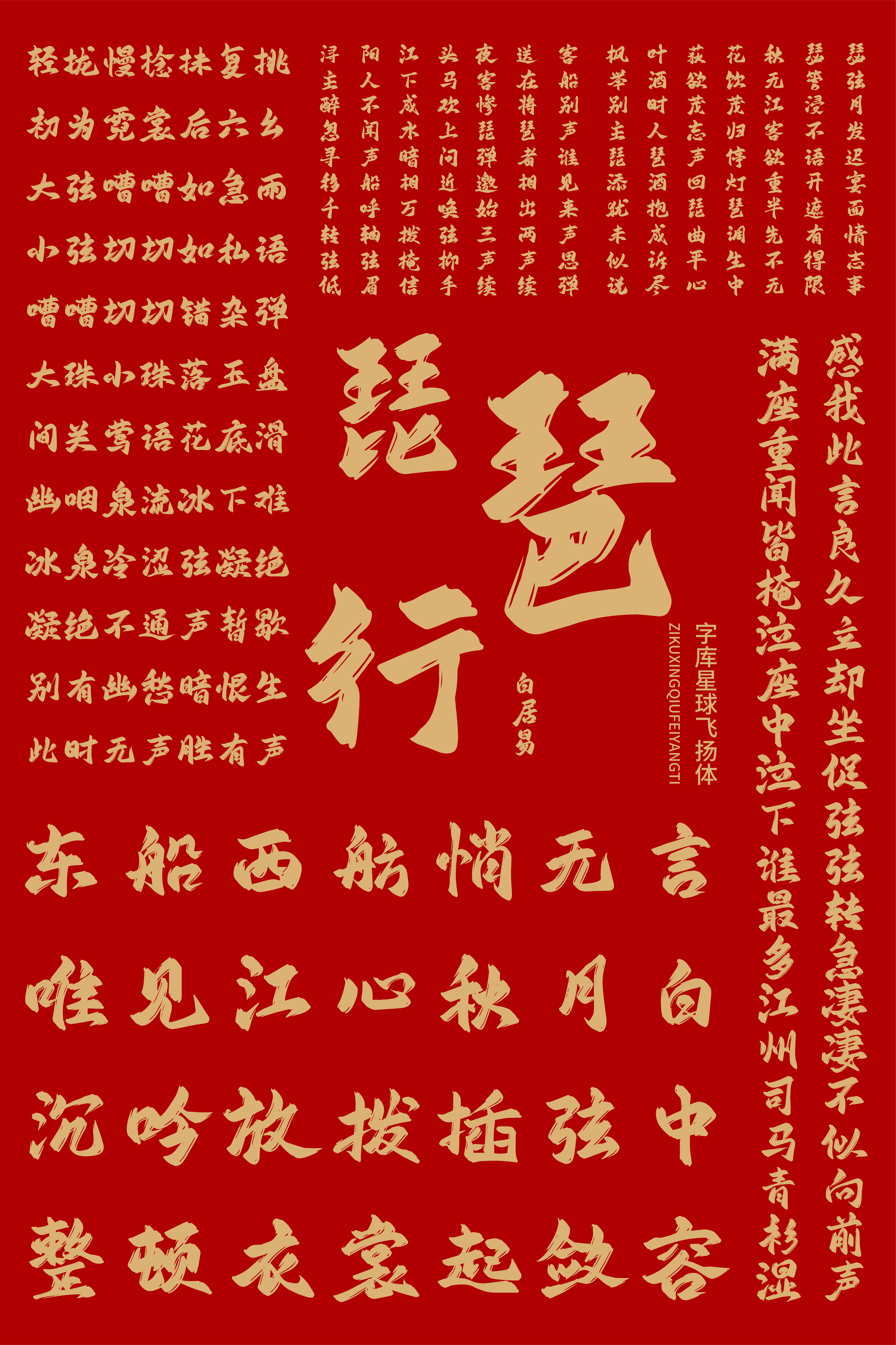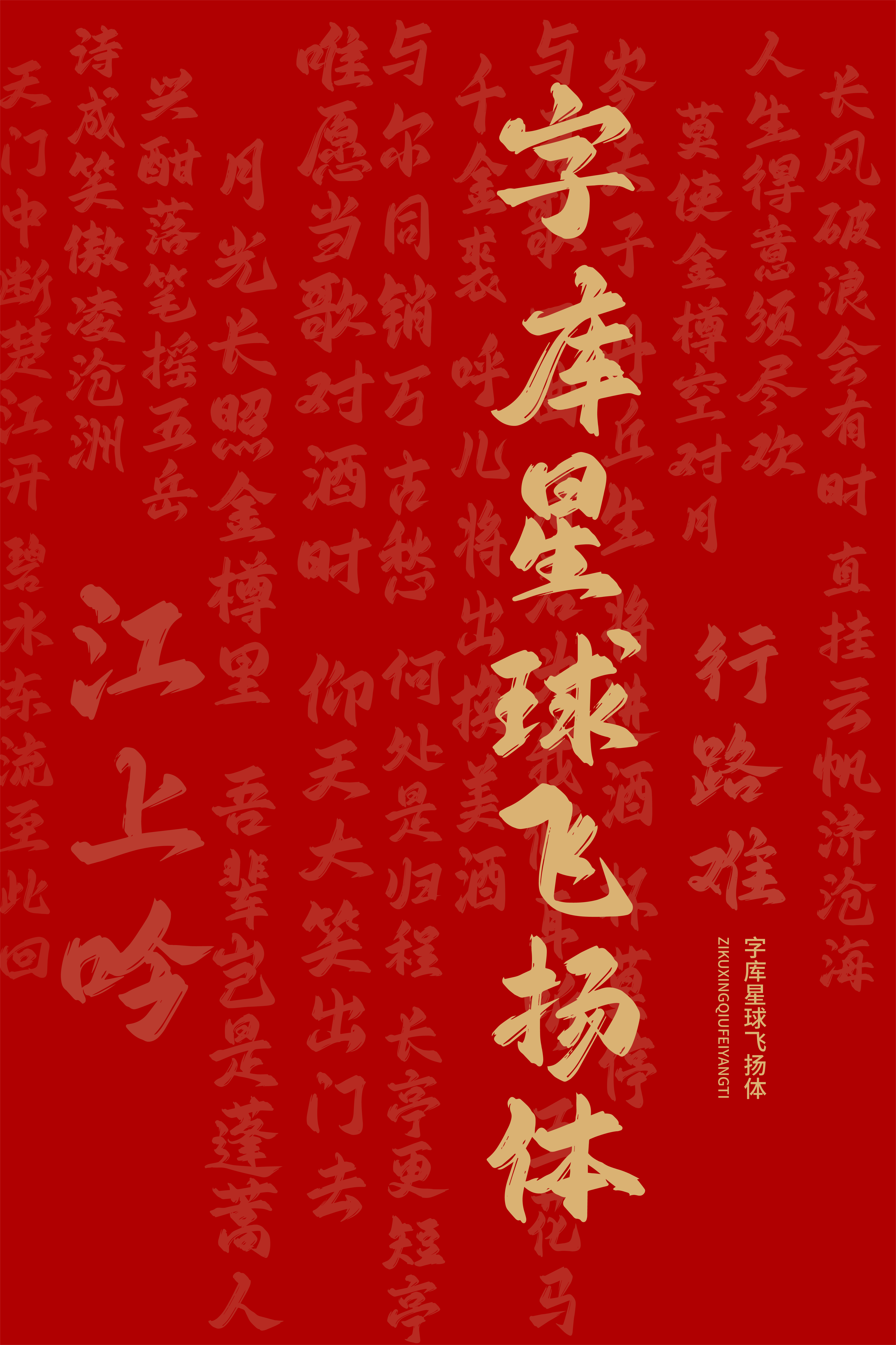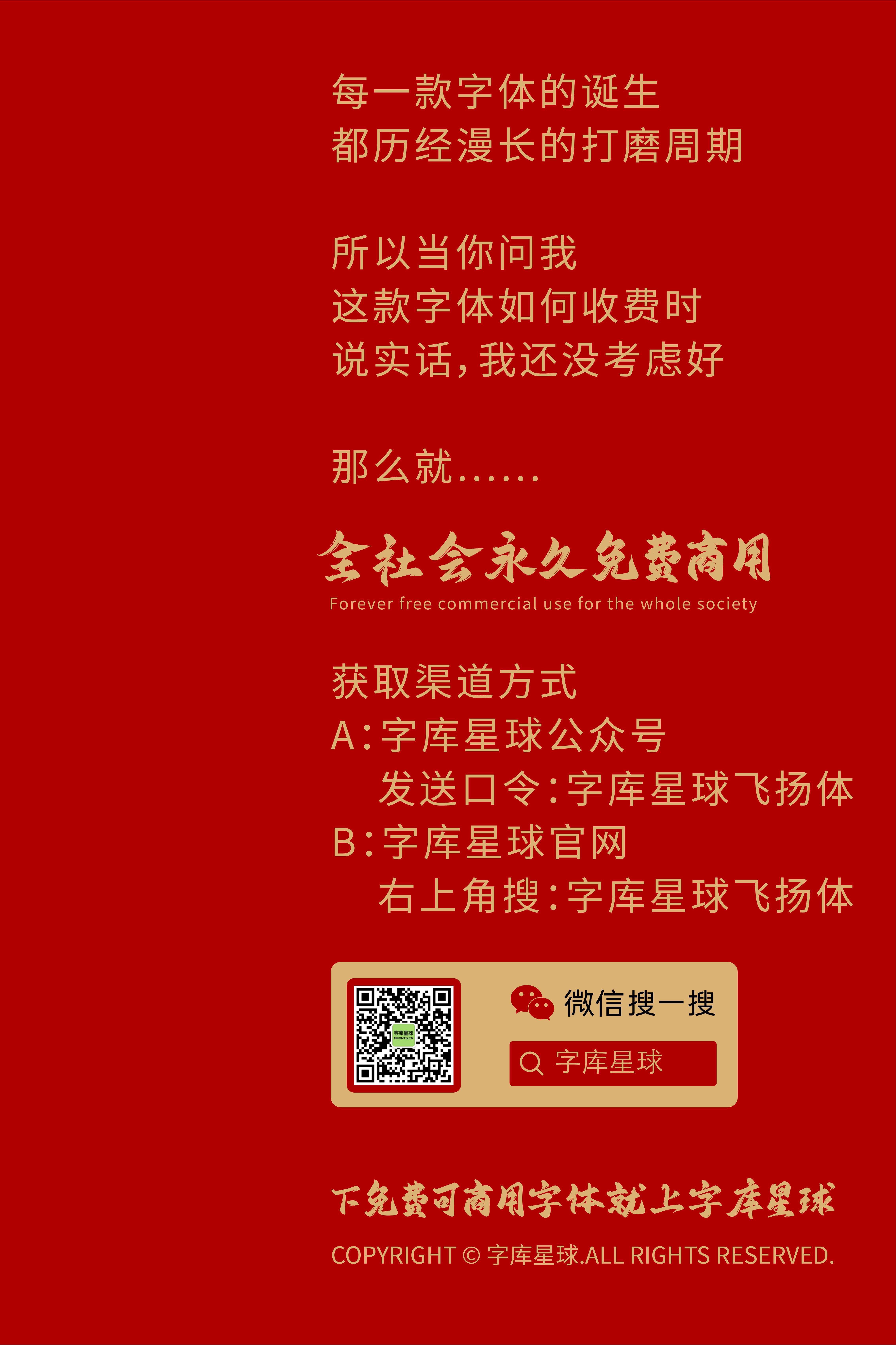
字库星球飞扬体字体信息
字库星球飞扬体
字体名称: 字库星球飞扬体
字体风格: 个性
字库星球飞扬体,是字库星球与甜奈网络深度合作、精心研发的一款书法字体。其融合传统书法美学与现代设计理念,呈现出潇洒写意、逸趣横生的独特风格。笔画灵动且富有变化,整体结构流畅自然,展现出别具一格的艺术气质,能够传递出飒爽流畅的视觉气场,有效烘托出热情洋溢的氛围。
字库星球飞扬体在诸多应用场景中表现广泛,尤其适用于标志 / 书籍 / 广告 / 杂志 / 动漫 / 游戏 / 影视 / 包装使用。在宣传类活动中,可强化热烈氛围,激发受众的参与热情;于文艺表演宣传方面,能够精准展现艺术内涵与魅力;在公益活动宣传里,能突出活动的积极意义与活力;用于文化周边产品,可赋予其深厚的文化底蕴;在各类节日庆典相关宣传中,更能营造出充满活力与喜悦的节庆氛围,全方位契合传统与现代融合的场景需求,助力打造极具吸引力的视觉呈现。